Trends in der Typografie
Wie Schriften genutzt werden, welche bei Kreativen am beliebtesten sind und warum manche nach heutigem Geschmack gar nicht mehr gehen, hat Extensis in einem Typografie-Report zusammengefasst. Die PDF gibt es kostenlos zum Downloaden.
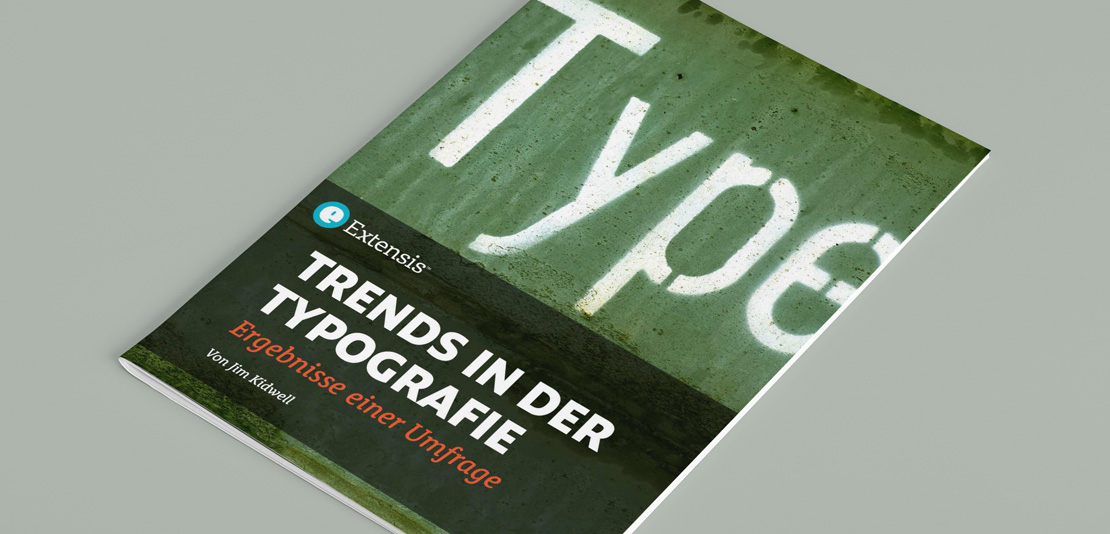
Der Report dokumentiert neben Fragen zu Trends auch, wie Designer Schriften finden, wofür sie diese einsetzen und welche Quellen für die Lizenzierung von Schriften bevorzugt werden.
Grundlage für die Erhebungen bildet eine Umfrage, an denen 1.900 Personen teilgenommen hatten – darunter befanden sich u.a. Font-Management-Kunden von Extensis sowie weitere Teilnehmer, die über Foren und Social-Media-Dienste zur Teilnahme animiert wurden.